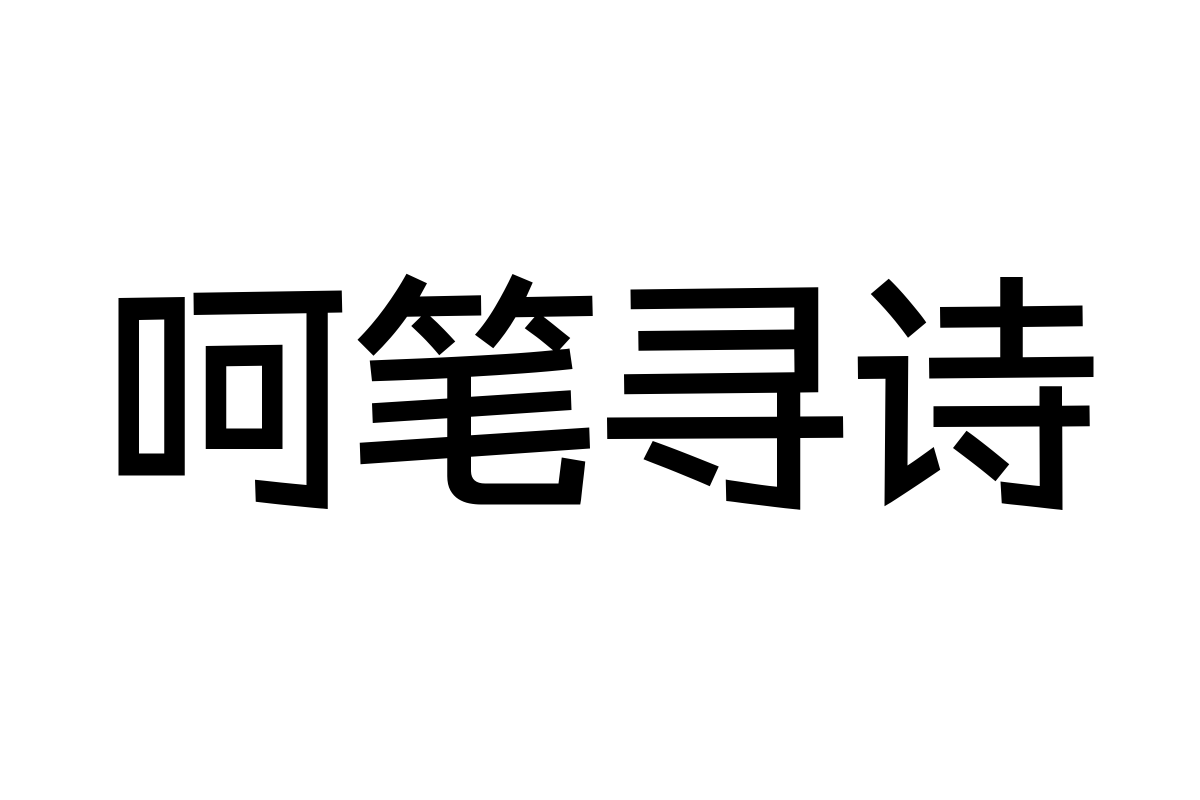
汉仪元隆黑-60是一款由汉仪公司推出的字体,具有独特的设计风格和广泛的应用场景。这款字体的特点是笔画粗细适中,线条流畅,给人一种简洁明快的感觉。同时,它的字形结构紧凑,易于阅读和识别,适用于各种文字排版和设计项目。
汉仪元隆黑-60的应用场景非常广泛,包括广告、海报、杂志、报纸、网站等各类媒体和产品包装设计。它能够很好地融入各种设计风格中,无论是现代简约还是复古文艺,都能够得到很好的展现。此外,这款字体还具有较强的可定制性,用户可以根据自己的需求进行个性化调整,以满足不同场合和风格的要求。